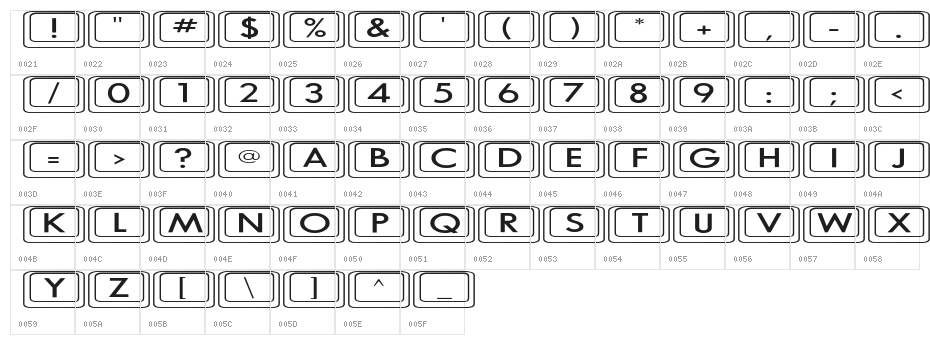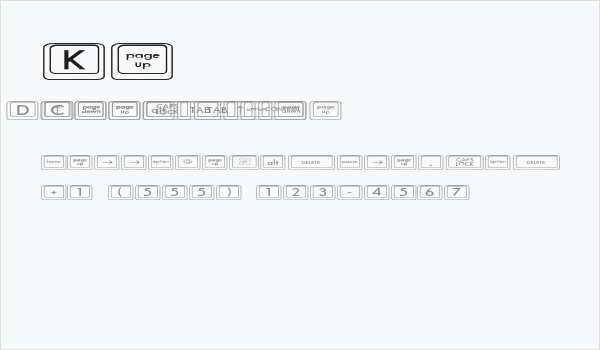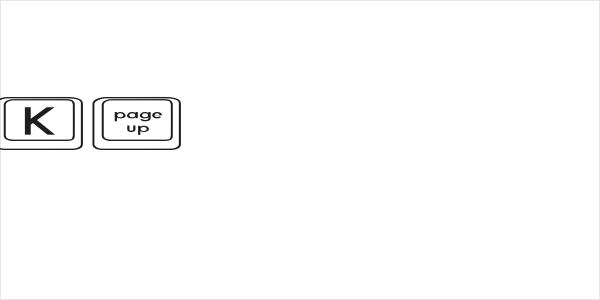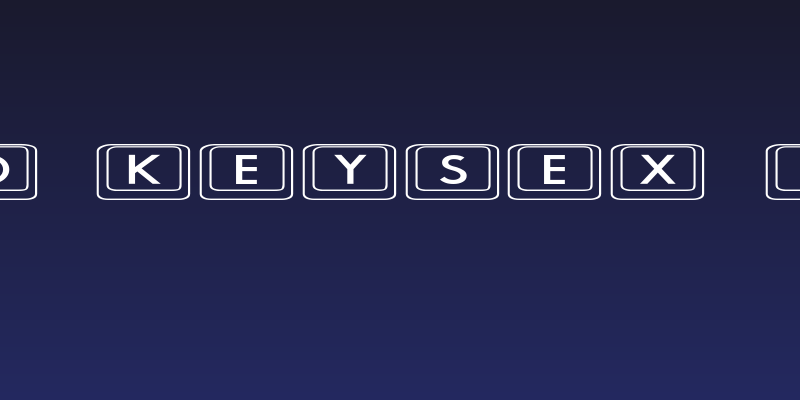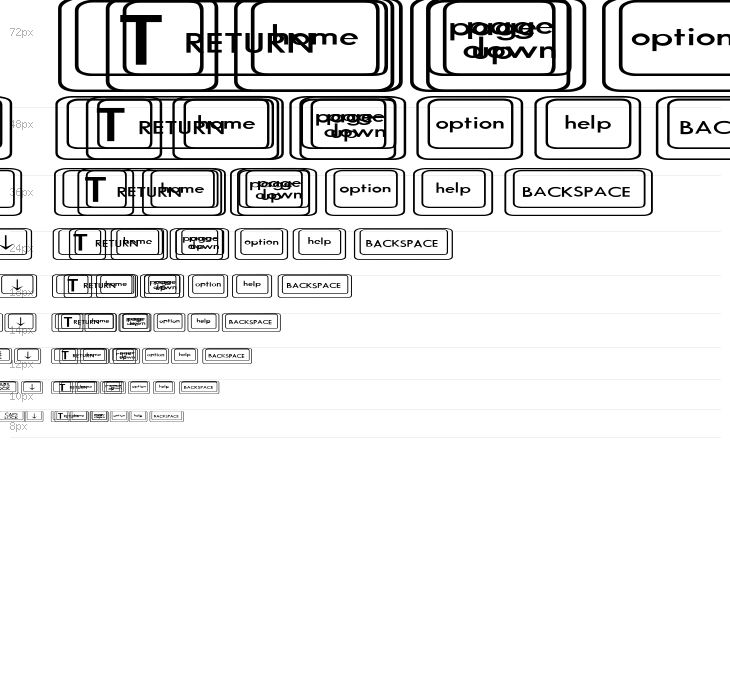
Keyboard KeysEx Expanded Font
| Caso d'uso | Logos, Headlines, Digital Interfaces |
| Progetti proposti | Ideal for tech-related designs, digital interfaces, educational materials, and any project needing a modern, digital aesthetic. |